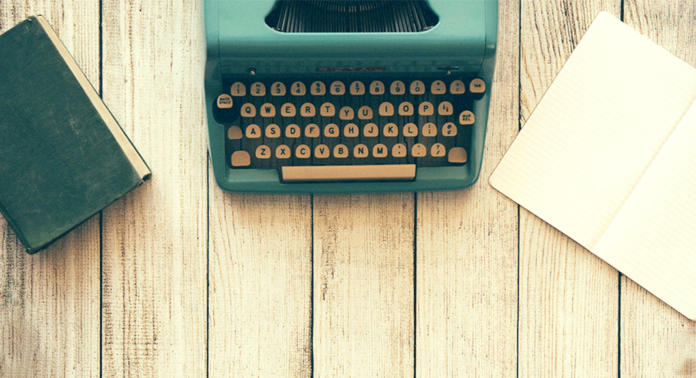
Der Monospace-Charakter ist allen Schreibmaschinen-Schriftbildern gemeinsam, stilistisch gibt es jedoch gewaltige Unterschiede. In unserer Auswahl zur Schriftart „Schreibmaschine“ bilden wir das gesamte Spektrum ab.
Adler
Das Schweizer Studio präsentiert mit seiner Schriftart eine Hommage an die erste deutsche Schreibmaschine: die „Adler 7“ des Fahrzeug- und Maschinenbauunternehmens Adlerwerke aus Frankfurt am Main, die um 1900 ein Verkaufsschlager war.
Cella
Dieser Font ist dem Schriftbild der gleichnamigen Reiseschreibmaschine nachempfunden, die bis in die 1980er-Jahre vom thüringischen VEB Robotron-Elektronik Zella-Mehlis produziert wurde.
Cuomotype
Basierend auf einer Schreibmaschinenschrift aus den 1970er-Jahren vermittelt dieser Font wegen seiner ausgefransten Lettern den Eindruck eines zu Ende gehenden Farbbands.
Cutive
Die Cutive orientiert sich an klassischen Maschinen-Schriftbildern, insbesondere an denen der „Executive“ von IBM und der „Smith-Premier“. Beide Schreibmaschinen kamen im ausgehenden 19. Jahrhundert auf den US-amerikanischen Markt.
Gabriele
Die Enkeltochter von Max Grundig gab der legendären Schreibmaschine ihren Namen, die von den 1950ern bis zu den 1980ern zum westdeutschen Büroalltag gehörte. Die leicht verwischten Buchstaben unterstreichen den nostalgischen Charakter der Schreibmaschinenschrift.
Larabiefont
Mit diesem Font lässt Raymond Larabie das Schriftbild der Schreibmaschine „Olympia Senatorial Nr. 71“ wieder aufleben.
Lekton
Inspiriert von den Schriftbildern einiger Olivetti-Schreibmaschinen erinnert das Designer-Team mit dieser Schriftart an das traditionsreiche Unternehmen. Die erste Schreibmaschine hatte Camilio Olivetti 1911 vorgestellt.
RM Typerighter
Charakteristisch für die Schrift RM Typerighter sind die filigranen Buchstaben. Etwas kräftiger gibt es diese Schriftart auch noch als RM Typerighter medium.
Special Elite
Schreibmaschinen-Stil für das Internet: Der Font, der an das Schriftbild der „Smith Corona Special Elite Type No NR6“ und der „Remington“ erinnern soll, ist für Webseiten optimiert.
Veteran Typewriter
Würde man für ein Krimi-Dinner mit Miss Marple werben, wäre dies die passende Typographie. Wie auf der mechanischen Schreibmaschine mit einem schwächelnden Farbband getippt wirkt dieser nostalgische Font.